Berikut kumpulan font gaming yang keren dan bisa Anda unduh dan install di PC / Laptop secara gratis!
Ingat logo game PUBG, Mobile Legends, dan FF yang viral itu? Logo-logo tersebut merupakan salah satu contoh terbaik bagaimana font gaming dapat memberikan identitas yang kuat dan daya tarik visual suatu merek. Saat ini, penggunaan font gaming juga tidak hanya terbatas pada industri game, namun juga meluas ke berbagai proyek desain lainnya.
Mulai dari poster hingga desain merchandise, font gaming memberikan kesan yang dinamis, modern, dan menghibur. Nah, apabila Anda sedang mencari font gaming gratis, dalam artikel ini, kami telah merangkum 36 rekomendasi font gaming keren yang bisa langsung Anda unduh dan gunakan secara gratis untuk mempercantik desain kece Anda. Yuk, simak daftarnya di bawah ini!
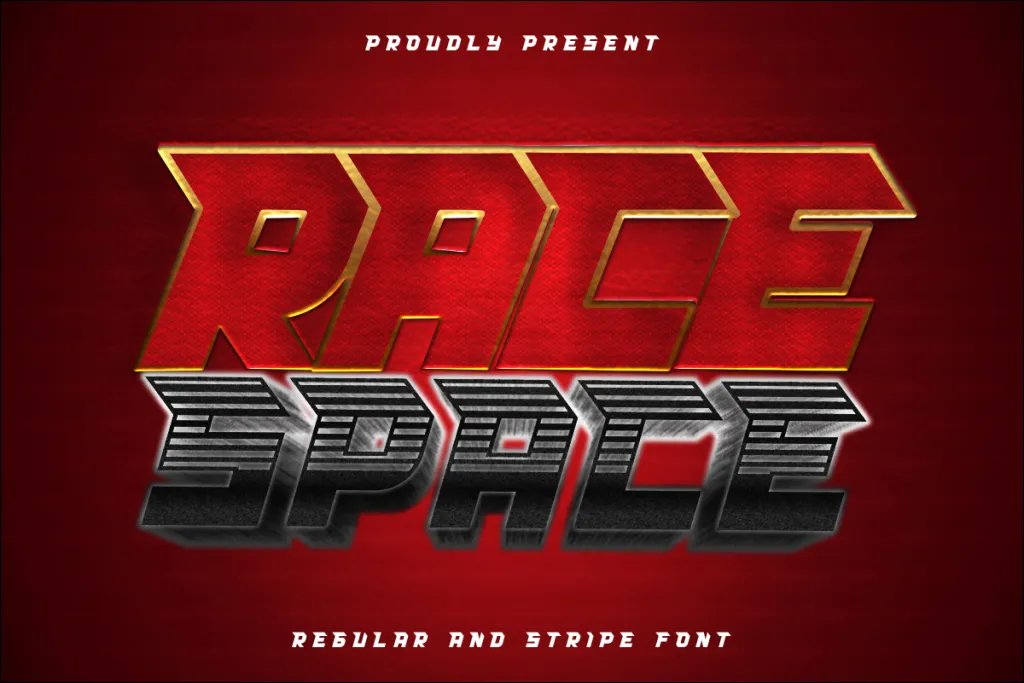
Font pertama adalah Race Space, font yang memiliki tampilan futuristik dengan garis-garis yang tajam dan modern, cocok untuk desain yang berfokus pada kecepatan, inovasi teknologi atau game balapan.
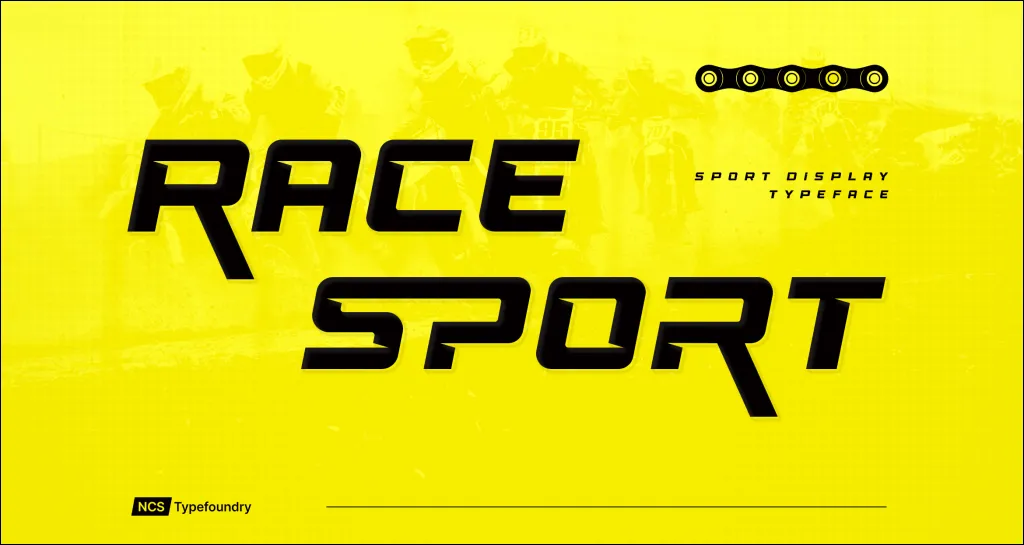
Font kedua adalah Race Sport, font yang menghadirkan desain techno modern dengan elemen-elemen yang terinspirasi dari dunia balap dan olahraga, cocok untuk desain poster atau logo yang mempromosikan aksi cepat atau balapan.
Selanjutnya adalah font Dash Horizon, font dengan tampilan tebal dan modern, memberikan kesan kokoh dan kuat pada desain Anda.
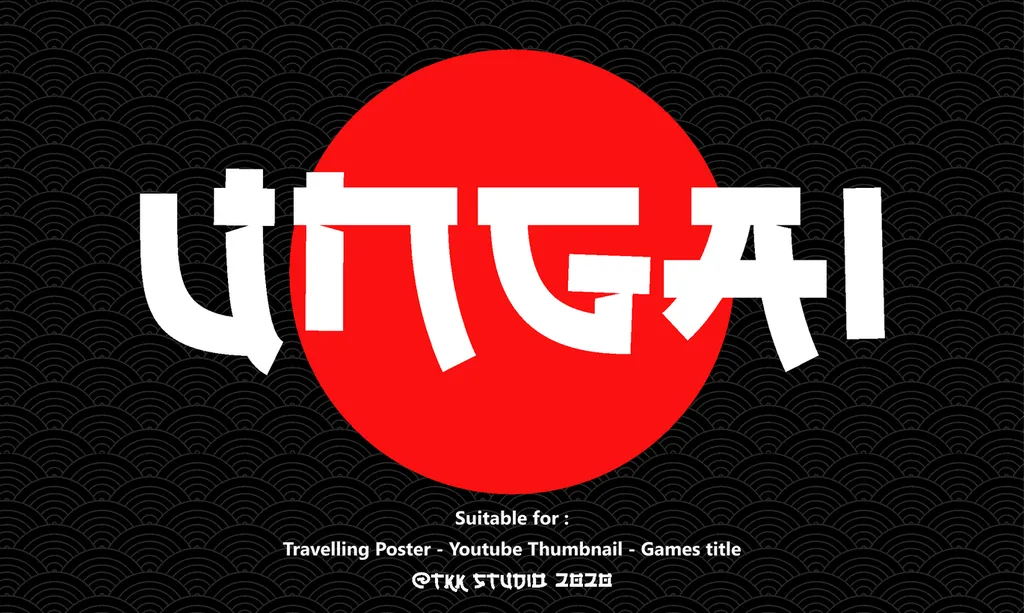
Ungai, font yang unik dengan karakter huruf yang terinspirasi dari alam liar, cocok untuk desain yang berhubungan dengan petualangan di hutan atau kegiatan luar ruangan.
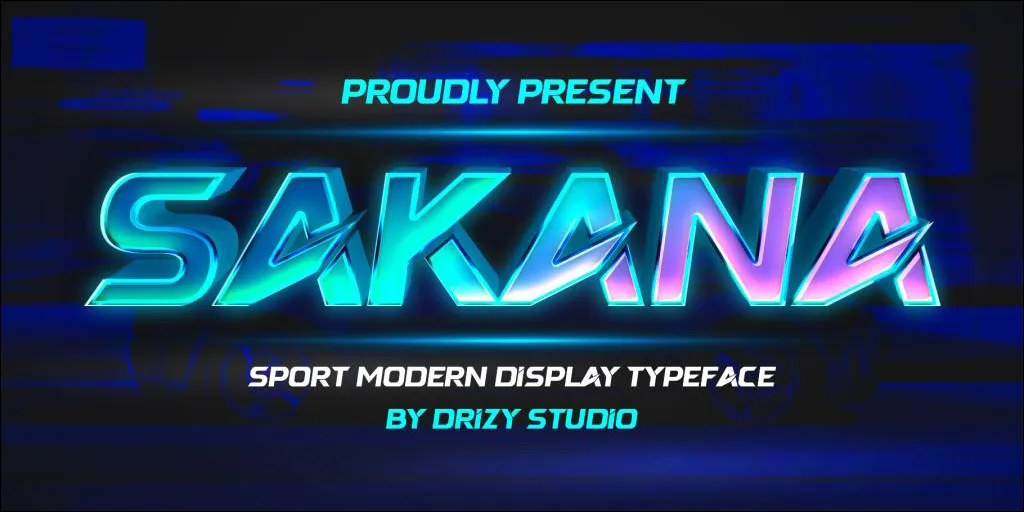
Font ini memiliki tampilan sporty modern yang terinspirasi dari dunia otomotif. Cocok digunakan untuk proyek desain yang berhubungan dengan otomotif.
Sebagaimana namanya, River Adventure merupakan font sans serif dengan desain yang mengingatkan pada petualangan, sehingga cocok untuk desain yang berhubungan dengan eksplorasi alam liar atau petualangan alam.
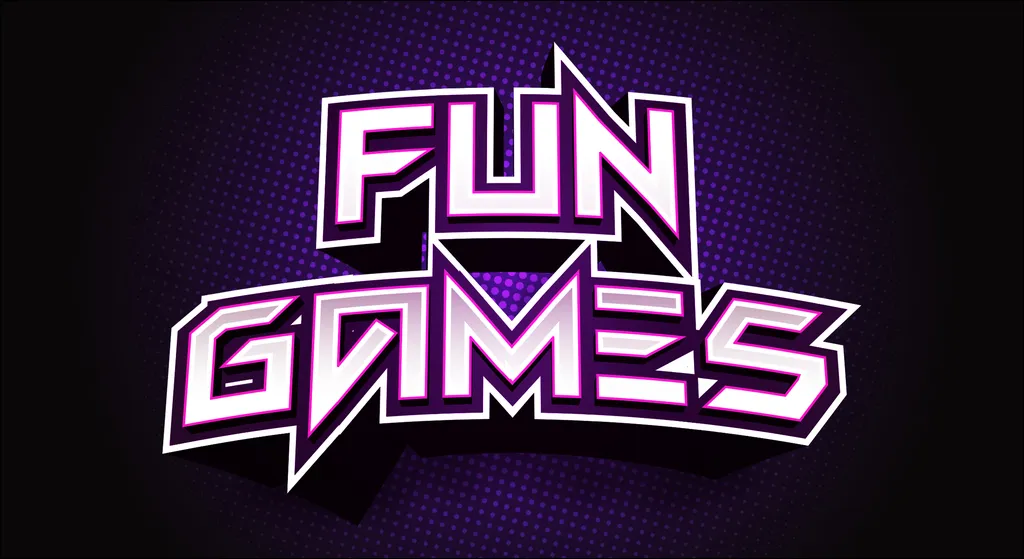
Font ini memiliki desain bold yang futuristik dan modern. Selain itu, font ini juga memiliki nuansa tekno, sehingga cocok digunakan untuk headline, desain UI, dan lain-lain.
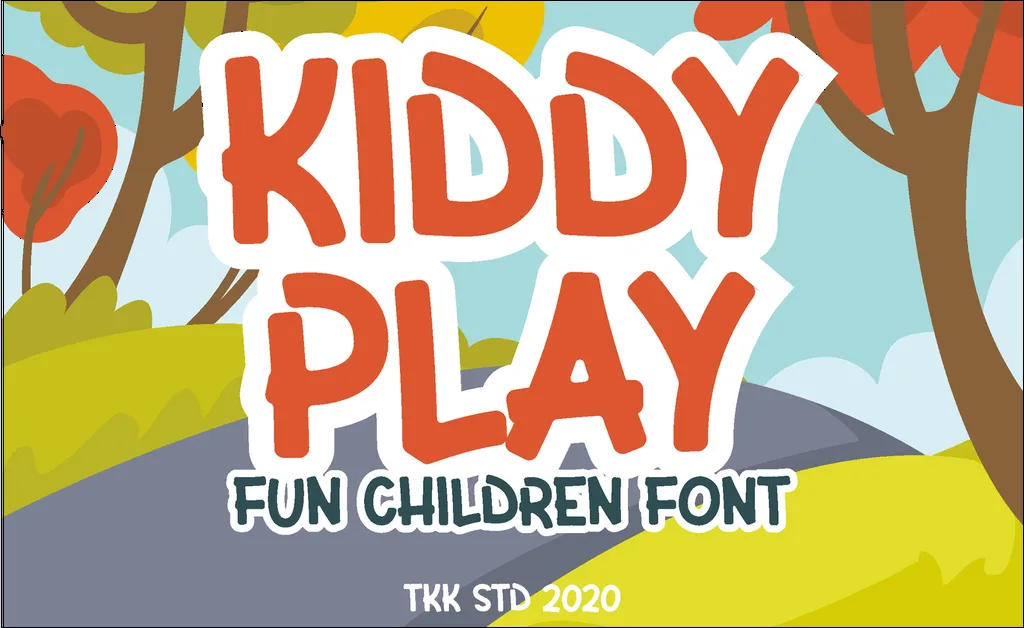
Font ini menghadirkan tampilan yang lucu dengan karakter huruf kotak-kotak dan sudut yang membulat, cocok untuk desain yang ditujukan kepada anak-anak atau produk yang mengusung tema keceriaan, seperti cover buku, poster, majalah, dan lain sebagainya.
Font ini hadir dengan estetika retro yang mengingatkan pada era game klasik, cocok untuk desain yang ingin menampilkan nuansa nostalgia dan kesan yang klasik.
Dengan tampilan yang misterius dan sedikit menyeramkan, font ini cocok untuk desain yang berhubungan dengan tema horor atau misteri.
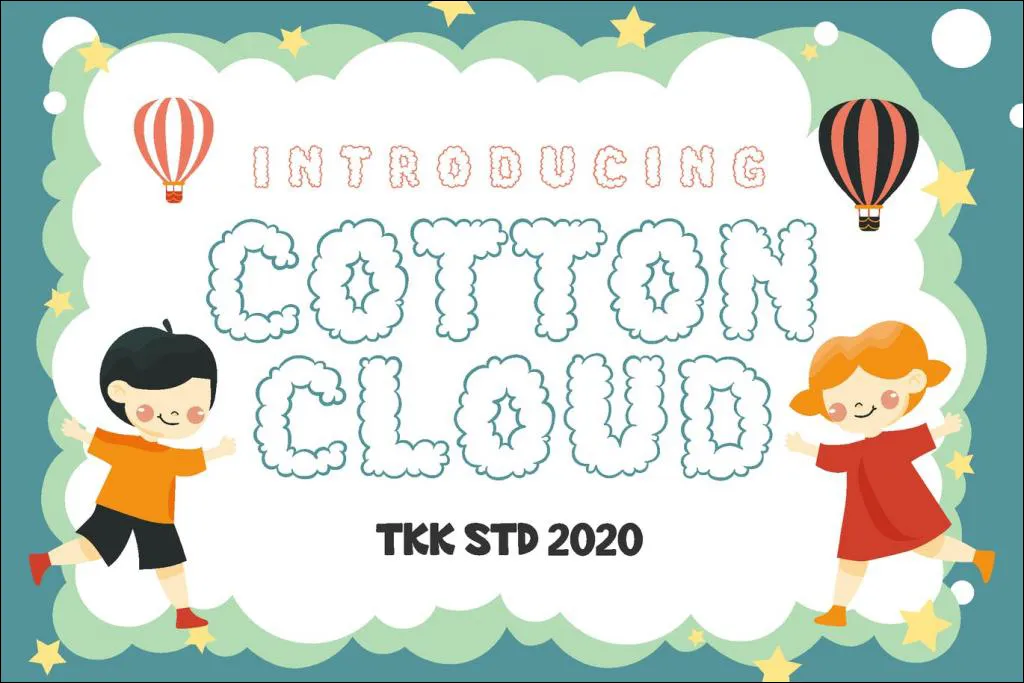
Cotton Cloud menampilkan karakter huruf yang lembut dan mengambang seperti awan, font ini cocok untuk desain yang ingin menekankan pada kesan ringan dan menyenangkan seperti game anak-anak atau poster perjalanan.
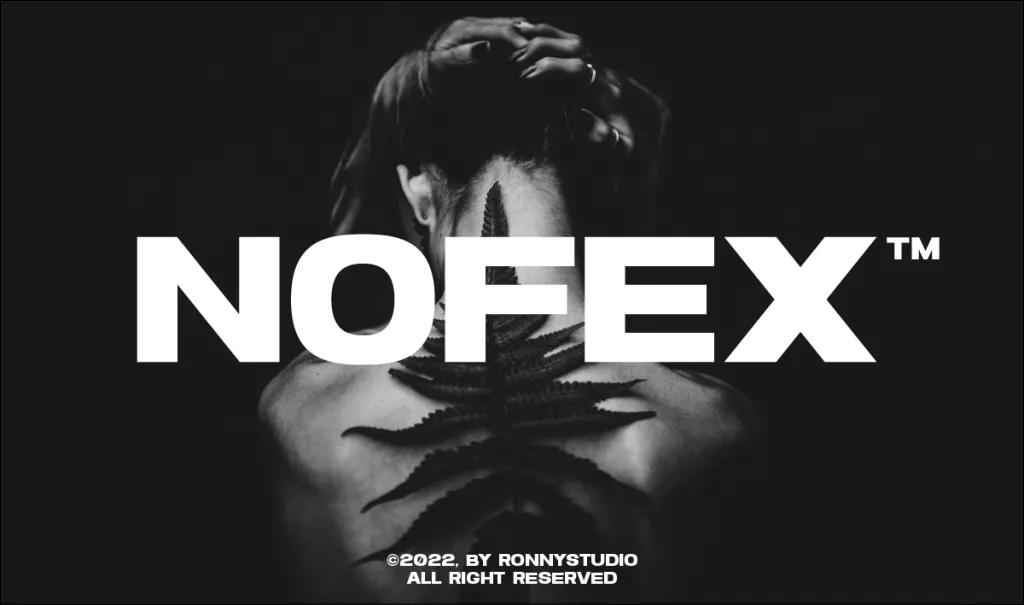
Dengan desain yang simpel dan modern, font ini cocok untuk berbagai desain yang membutuhkan tampilan yang bersih dan mudah dibaca.
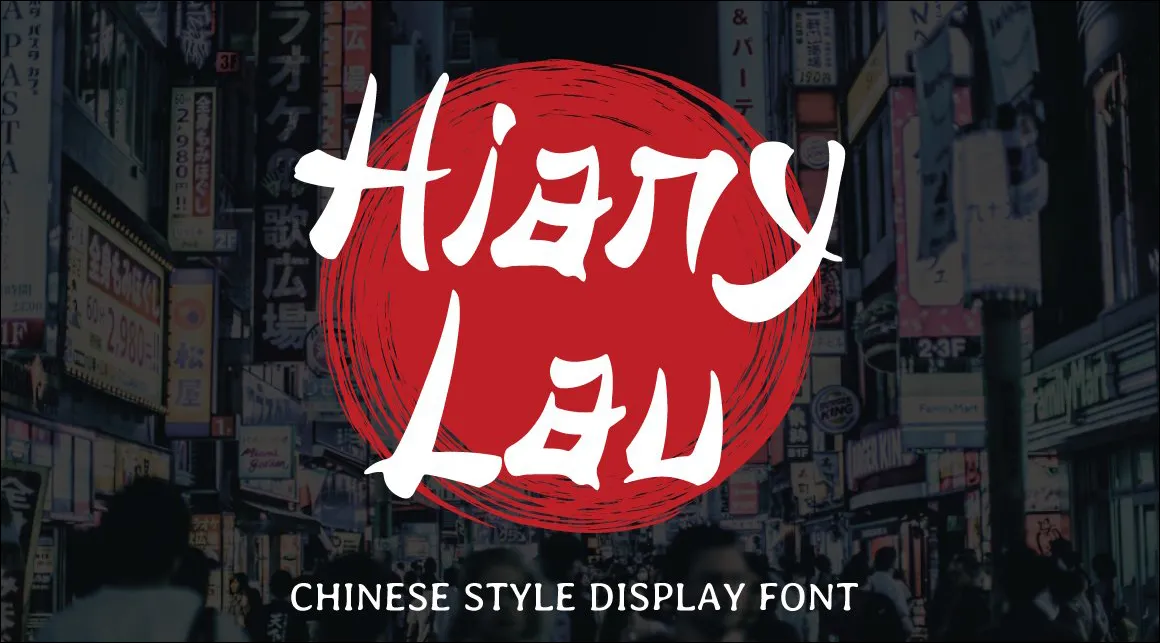
Font ini menghadirkan sentuhan artistik dan misterius dengan karakter huruf yang terinspirasi dari tulisan tangan China, cocok untuk desain yang ingin menampilkan kesan personal dan unik.
Dengan tampilan yang ajaib dan misterius, font serif ini cocok untuk desain yang berhubungan dengan dunia sihir dan fantasi, seperti poster acara magis, dan lain-lain.
Voltec merupakan font yang bersudut tajam dengan tampilan futuristik dan teknologis yang cocok untuk desain yang ingin menampilkan kesan modern dan canggih.
Font ini memiliki desain italic, terinspirasi dari modern sport dengan karakter huruf yang kuat dan tegas, cocok untuk berbagai macam desain.
Henshin menghadirkan tampilan font katana Jepang yang dinamis dan modern dengan sentuhan futuristik, font ini cocok untuk desain game battle/action atau merchandise.
Font ini memiliki tampilan yang lucu dengan sentuhan musim dingin yang khas, cocok untuk desain yang berhubungan dengan liburan musim dingin atau yang lainnya.
Font ini menghadirkan tampilan yang kuat dan kokoh dengan karakter huruf yang berdesain modern, cocok untuk desain headline, cover film/game, logo, label, desain otomotif, dan lain sebagainya.
Dengan desain yang mengingatkan pada gaya retro dan arcade, font ini cocok untuk desain yang ingin menampilkan nuansa klasik dan nostalgia dalam game.
Pertama, pertimbangkan karakteristik dan tujuan desain Anda. Pilih font yang sesuai dengan pesan yang ingin disampaikan. Selain itu, pastikan kesesuaian antara font gaming yang dipilih dengan tema dan estetika keseluruhan desain.